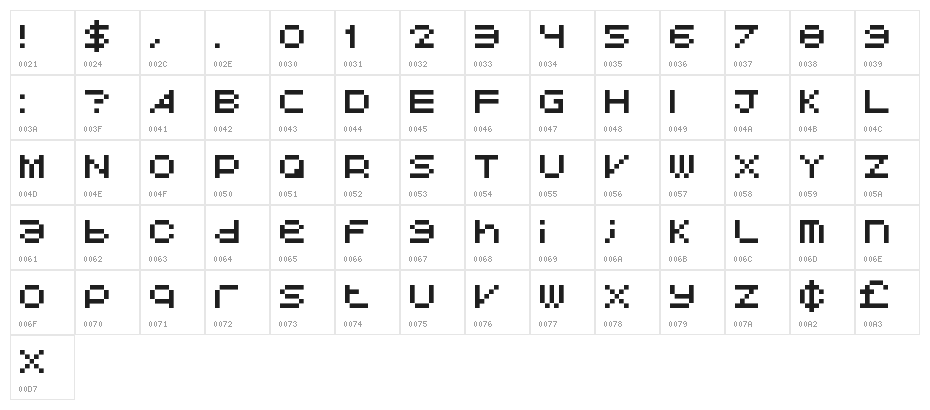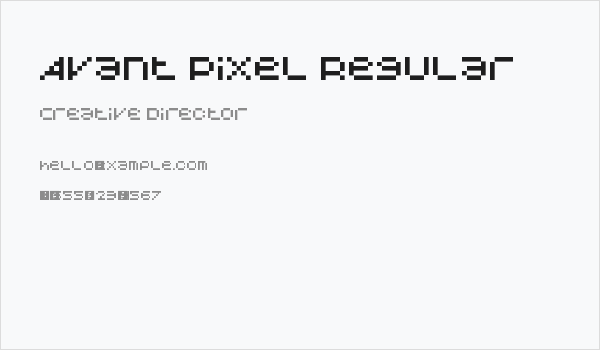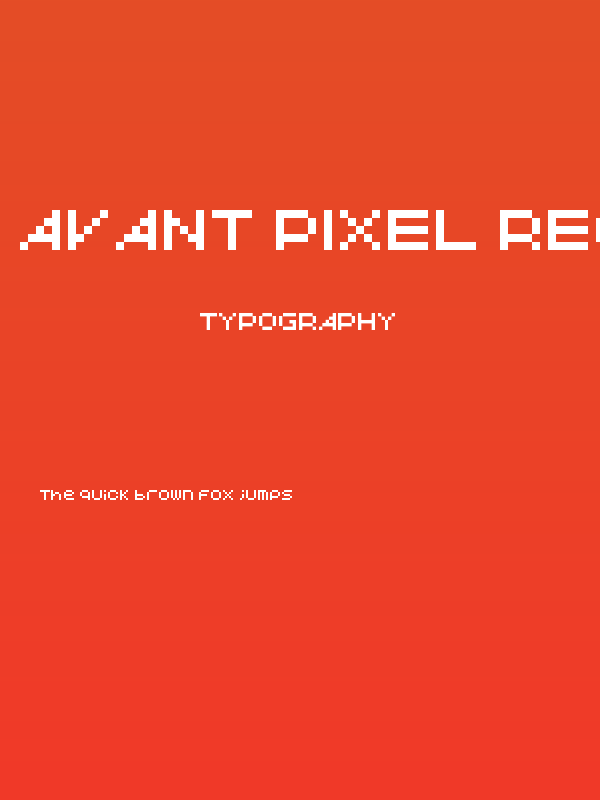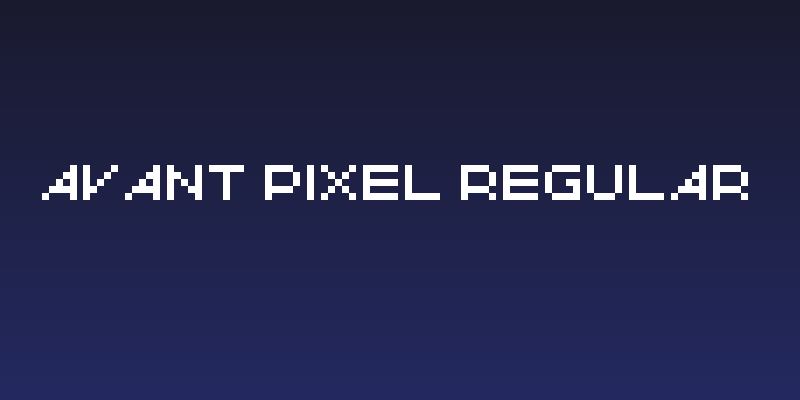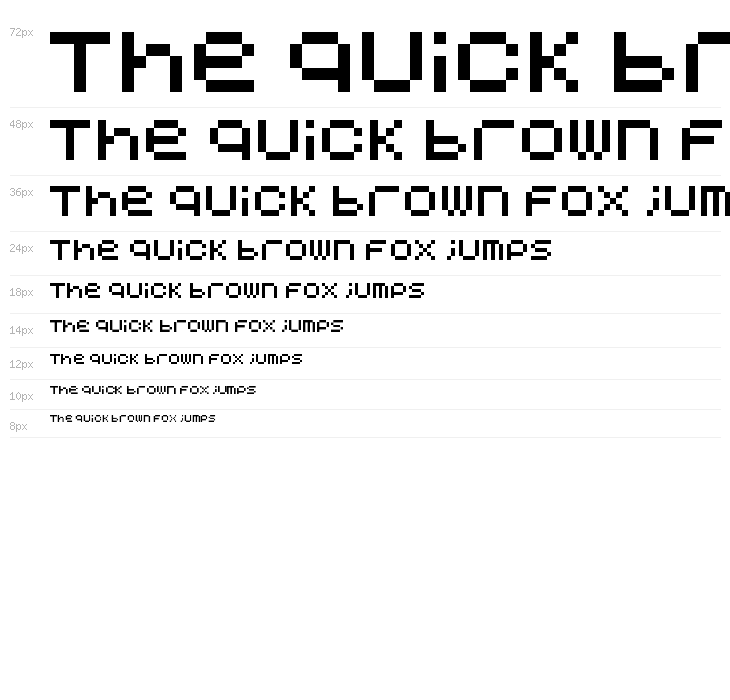
Avant Pixel Regular Font
| Stile generale | Retro, Digital |
| Caso d'uso | Headlines, Logos, Digital Art |
| Progetti proposti | Ideal for retro-themed designs, video game graphics, digital art projects, and any creative work that seeks to evoke a sense of nostalgia for early computing. |